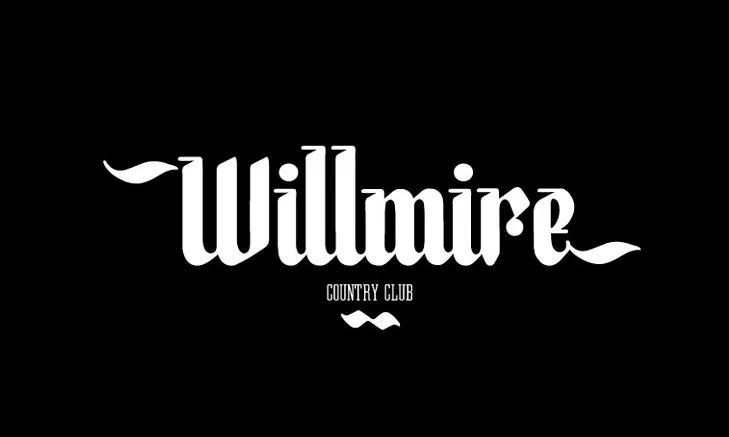
A fonte Mortyr Black é uma escolha perfeita para quem busca elegância masculina e clássica em seus materiais impressos. Criada pelo designer Hamilton, esta fonte atende ao coração de muitos amantes do estilo blackletter. Com um enredo que traz scripts inusitados, Mortyr se destaca por sua mistura de masculinidade e elegância clássica, tornando-se uma opção ideal para destacar rótulos ou outros materiais impressos. Não importa o design, Mortyr Black é capaz de transformar qualquer projeto em algo excepcionalmente sofisticado e impecável. Se você procura um toque único que reflete seu estilo, Mortyr Black certamente se encaixa perfeitamente no seu arquivo fonte.